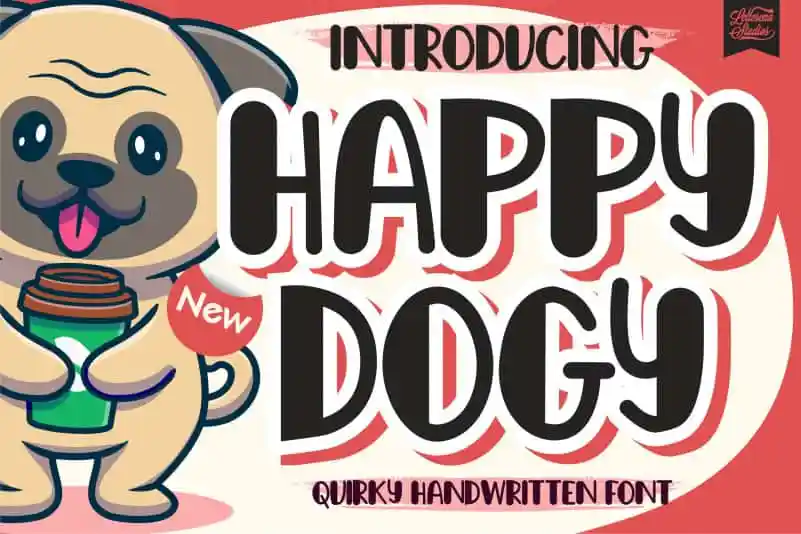
Happy Dogy Display Font – Download Grátis
A Happy Dogy Display Font é uma fonte à display que traz uma aparente inocência com sua aparência peculiar e única. Ela se destaca por seu estilo lúdico, ideal para aqueles projetos DIY imaginativos onde a leveza e a vivacidade da criança ganham vida. É essa mistura de simplicidade e criatividade que tornam esta fonte perfeita para qualquer iniciativa visual criativa. Adote-a para dar uma pitada de brincadeira ao seu design, seja ela um título ou um texto interno; a Happy Dogy Display Font será sua amiga fiel no processo de transformar seu trabalho em algo ainda mais emocionante e inusitado.